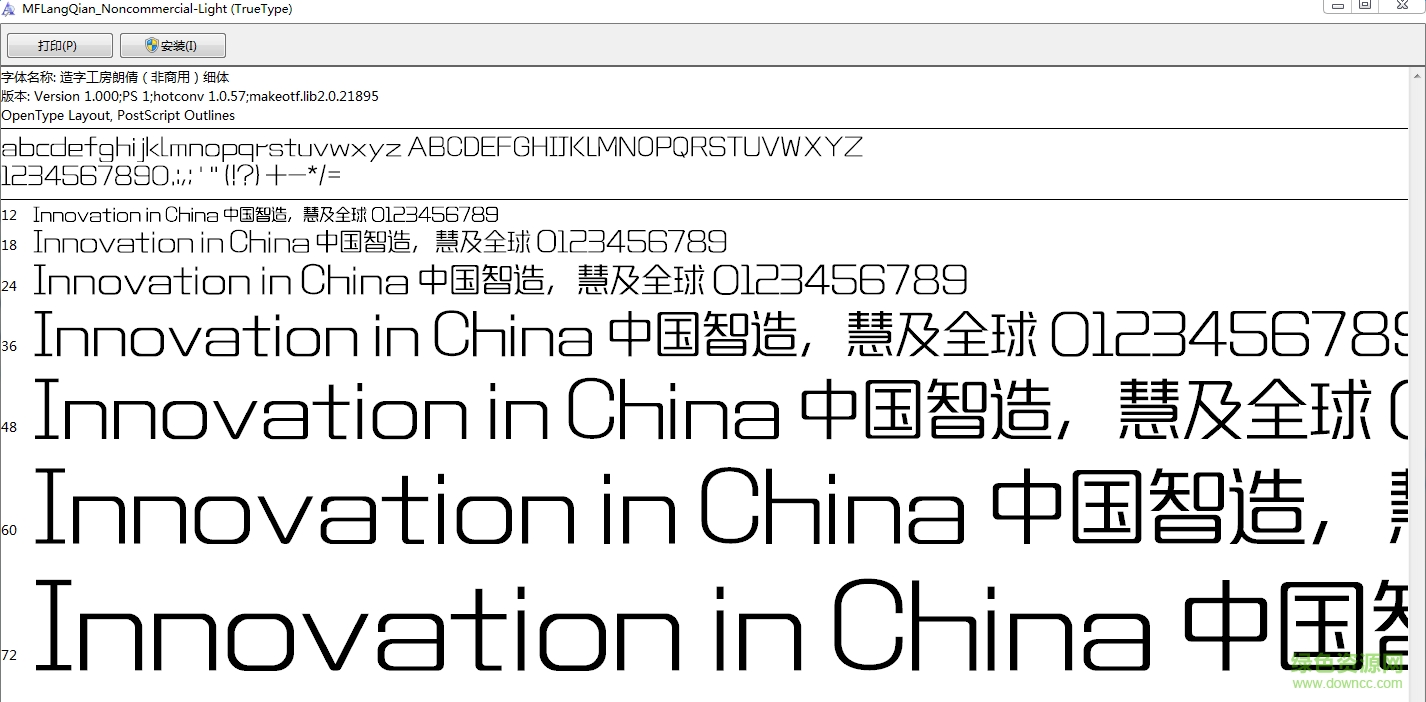
造字工房朗倩細體字體
造字工房朗倩細體是一款造字工房類古典清新風格字體軟件,朗倩細體給人非常簡單自由的感覺,其細細的字體有著較深的文章正文書寫應用,也深受廣大書法家的喜愛,還有更多好看字體盡情期待,歡迎到綠色資源網(wǎng)下載體驗!
字體介紹
造字工房朗倩細體應用于藝術設計方面的字體,字形美觀大方,其筆畫的設計在直線與曲線有著良好的平衡取舍關系,適用于標題、副標題等視覺環(huán)境。